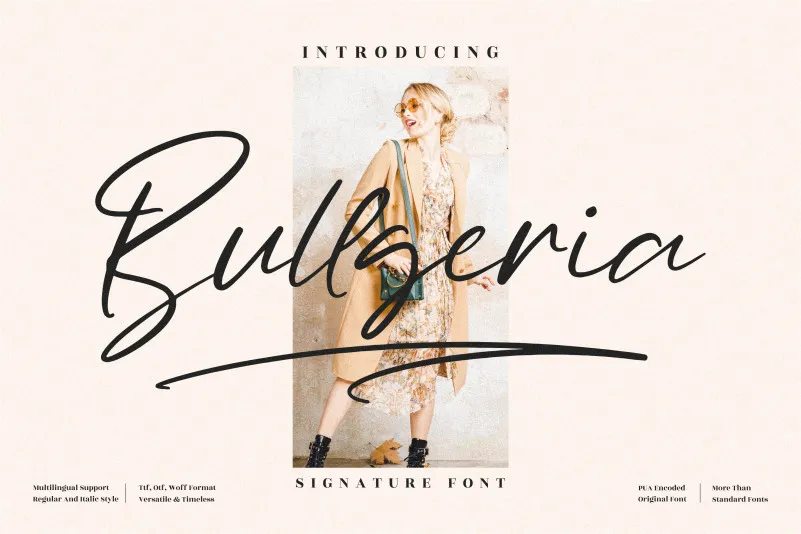
A fonte ‘Bullgeria Font’ é uma elegante tipografia à mão escrita ideal para designers que procuram uma mistura delicada e minimalista. Com seu design limpo, finamente detalhado e suave, ela traz um toque sofisticado a qualquer projeto. Ideal para aplicar em logotipos ou texturas, o Bullgeria Font oferece um conjunto completo de caracteres e swashes que podem ser facilmente acessados com sua PUA (Propriedade Unicode) encodada. Com seu estilo elegante e delicado, é uma fonte perfeita tanto para design gráfico quanto para criação de materiais digitais. Suas linhas finas e clean trazem um ar sofisticado ao texto, tornando-o o ideal para incorporar em designs que buscam transmitir elegância e refinamento. O Bullgeria Font é uma fonte PUA encodada, garantindo que todos os caracteres e swashes estejam disponíveis para uso com facilidade, facilitando a criação de projetos incríveis que combinam estilo e funcionalidade.